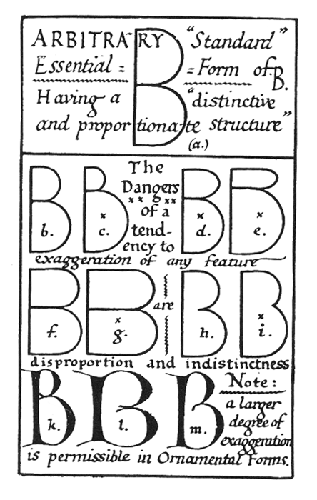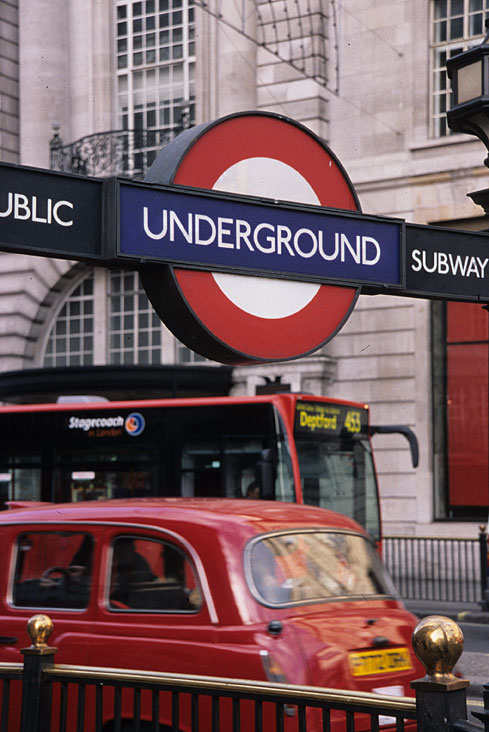
Edward Johnston (1872-1944)
O formador, calígrafo e typeface designer britânico foi o autor da famosa London Transport. Com este tipo fundou a tradição da «humanist sans-serif»Edward Johnston desenhou em 1916 uma fonte tipográfica sem serifas para o metro de Londres, a "Johnston", actualmente "Underground", que está presente na famosa imagem da actual rede urbana do metropolitano londrino.
Johnston foi um dos muitos seguidores das doutrinas estéticas de William Morris.
Através dos estudos e pelos trabalhos práticos realizados, Johnston recebeu (em 1916) de Frank Pick a encomenda de conceber a letra e o sistema sinalético do London Underground. A fonte que concebeu, a London Transport, continua em uso (com ligeiras modificações), no sistema de transportes urbano que 8 milhões de londrinos chamam Tube. A London Transport é uma das grotescas clássicas do século XX; além dos caracteres comuns, existem os Extras - glifos para a legendagem e para o traçado dos percursos nos mapas do metropolitano londrino. Eric Gill foi aluno, camarada e admirador do desenhador de letras Edward Johnston. Ambos, mestre e discípulo, dedicaram-se ao estudos de letras lapidares, ambos eram apreciadores convictos das letras renascentistas. LinksA Fundação Edward Jonston, presidida por Hermann Zapf, guarda o seu legado promovendo o estudo e a prática da caligrafia. www.ejf.org.uk BibliografiaHeitlinger, Paulo. Tipografia: origens, formas e uso das letras. Copyright © 2006 Paulo Heitlinger, ISBN 10 972-576-396-3 , ISBN 13 978-972-576-396-4, Depósito legal 248 958/06. Dinalivro. Lisboa, 2006. Página actualizada em 08.07.2007 |